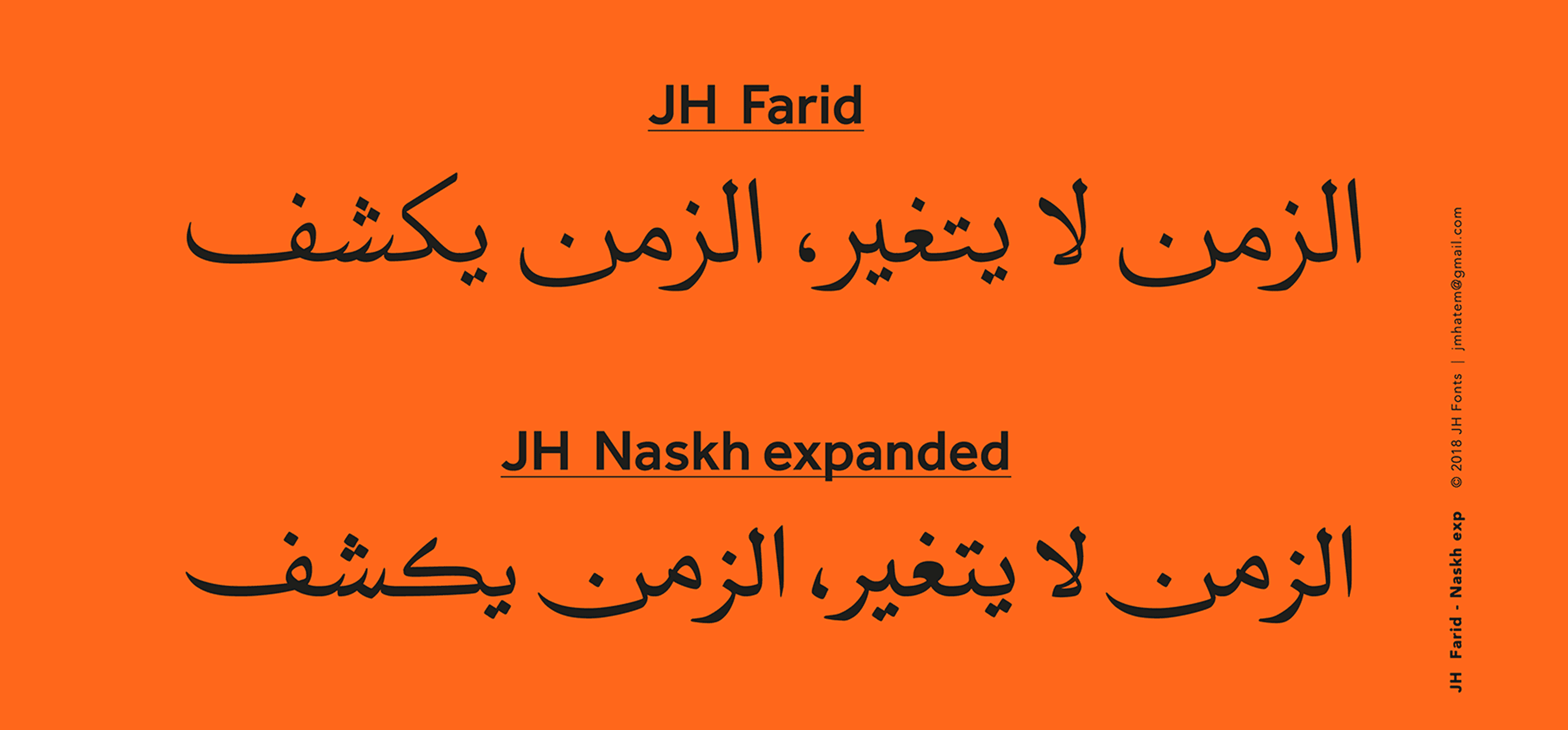
خط JH Naskh Expanded هو خط عربي مستوحى من أسلوب النسخ الكلاسيكي، لكن بتوسعة واضحة في عرض الحروف، مما يمنح النص توازنًا بصريًا وأناقة في التكوين. يتميّز الخط بجمالياته المتقنة ووضوحه العالي مما يجعله مثاليًا للاستخدام في العناوين، الكتب، والمجلات، وكذلك في التصاميم الإعلانية.